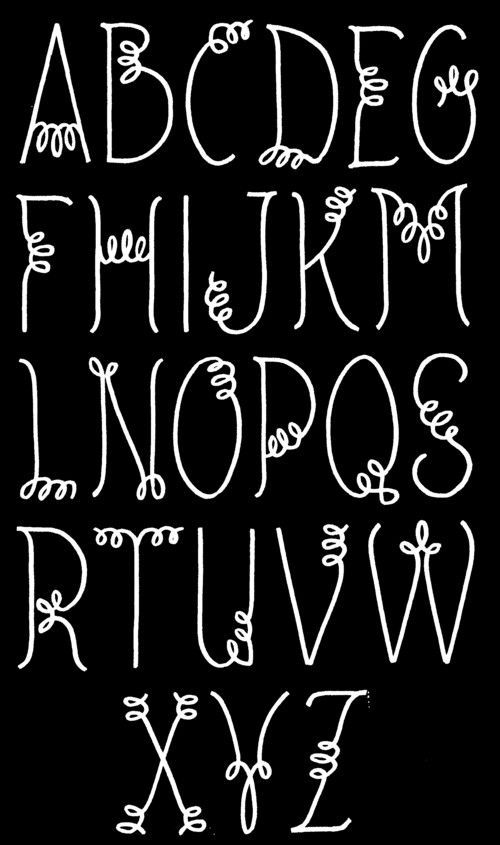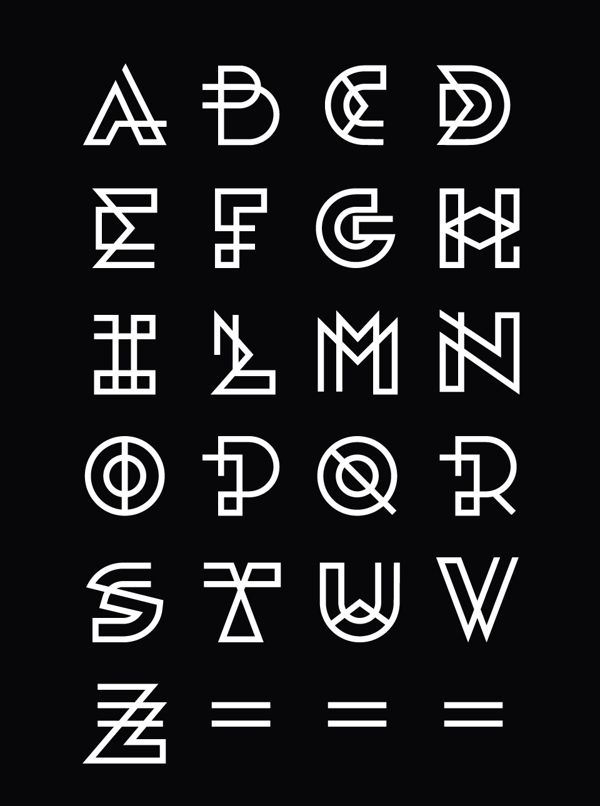
Оригинальные шрифты для заголовков: лучшие шрифты для отличных заголовков
Некоторые из лучших дизайнов состоят из лучших шрифтов. И не следует ожидать, что эти шрифты представляют собой совокупность этого представления. Если вы увлечены миром шрифтов и типографского дизайна, это пост, который вы, несомненно, искали.
В этом посте мы пришли не только поговорить с вами о том, какая типографика лучше всего подходит для вашего проекта, но и, мы покажем вам некоторые из самых выдающихся семей, таким образом, вы будете знать различные существующие типы, чтобы позже использовать их в своих проектах.
семейства шрифтов
Когда мы говорим о семействах шрифтов, Мы говорим о том, как шрифты распространяются или каталогизируются в дизайне. Например, одни шрифты отличаются от других из-за их формы, а другие, с другой стороны, из-за того, что они передают.
- Роман
- Пало Секо
- помечен
- Декоративные
Это были первые 4 категории шрифтов, теперь мы увидим категории, на которые разделен этот тип шрифтов.
Роман
В римской группе мы находим пять подкатегорий или типов римского языка.
- антигуас
- Переход
- Модерн
- конструкторы
- Надрезанный
Римляне тоже Они известны как шрифты с засечками. потому что они содержат очень ярко выраженные засечки в своих формах. У них довольно традиционный дизайн, поскольку они были первыми шрифтами, разработанными, особенно во времена Римской империи, вырезанными из камня.
Они очень полезны, если вы ищете классический и серьезный вид. Кроме того, они обычно понимают 95% бегущих текстов многих книг или заголовков из-за их высокой читабельности.
Сухая палка
Если мы говорим о шрифтах без засечек, мы находим две основные подкатегории.
- гротеск
- Линейный
Шрифты без засечек тоже Они известны как шрифты без засечек. что, в отличие от римских, они отличаются тем, что не содержат в своих рисунках выделенных засечек.
Это шрифты, которые также выделяются своим инновационным и современным внешним видом.
помечен
В помеченном разделе мы находим еще три подкатегории:
- каллиграфический
- Готика
- курсив
Эти шрифты характеризуются также за то, что они известны или называются рукописными или рукописными шрифтами. Их внешний вид делает их довольно творческими или художественными шрифтами. И его использование происходит только от крупных заголовков, так как неразборчивые шрифты для бегущего текста. Они также часто применяются в дизайнах, таких как плакаты или открытки для определенных церемоний.
Декоративные
В декоративных фонтанах мы находим две основные группы:
- Фантазия
- время
Это, несомненно, самые художественные шрифты, поскольку в зависимости от того, как они разработаны, они могут быть получены из определенных жанров или различных типологий проектов.
Одним из очень заметных доказательств является логотип Disney.
Примеры шрифтов для заголовков
Губернатор
Governos считается очень креативным и ярким шрифтом без засечек, поскольку он создает и вызывает ассоциации с некоторыми заведениями, типичными для некоторых магазинов в Майами. представленный в то время таким дизайном, как ар-деко.
Он считается довольно дружелюбным шрифтом благодаря своим формам и дизайну. Кроме того, он имеет толщину, которая во многом его характеризует и превращает в собственный шрифт для анимированных и очень личных проектов. Без сомнения, если вы ищете шрифт, с помощью которого хотите привлечь внимание, это, несомненно, указанный шрифт.
верховный
Suprema, пожалуй, самый интересный геометрический шрифт во всей библиотеке, которую мы вам покажем. Она очень похожа на знаменитую Futura Пола Реннера, и не то, это придает очень элегантный и дружелюбный вид вашим проектам.
Еще один аспект, который сильно характеризует этот шрифт, заключается в том, что он имеет высокий диапазон разборчивости, что делает его подходящим для любого типа текста. Не оставайтесь без этого типа шрифта, так как он довольно креативен и, прежде всего, очень, очень оригинален и привлекателен.
Лунная поляна
Приветствую всех в типографике будущего или космоса. Это шрифт, который благодаря своему дизайну считается одним из самых современных и современных. Кроме того, он содержит такие тонкие линии, что они полностью подходят и предназначены для чтения. Это обычно очень хорошо сочетается в средствах массовой информации, таких как плакаты, даже в фирменном стиле, так как его дизайн очень творческий и индивидуальный, чтобы быть представленным в логотипах. Если вы все еще ищете шрифт, который сделает ваши проекты проще и еще более удивительными, вы, без сомнения, не можете его пропустить.
Идеально сочетать прописные и строчные буквы, так как орнамент прописных букв как живой.